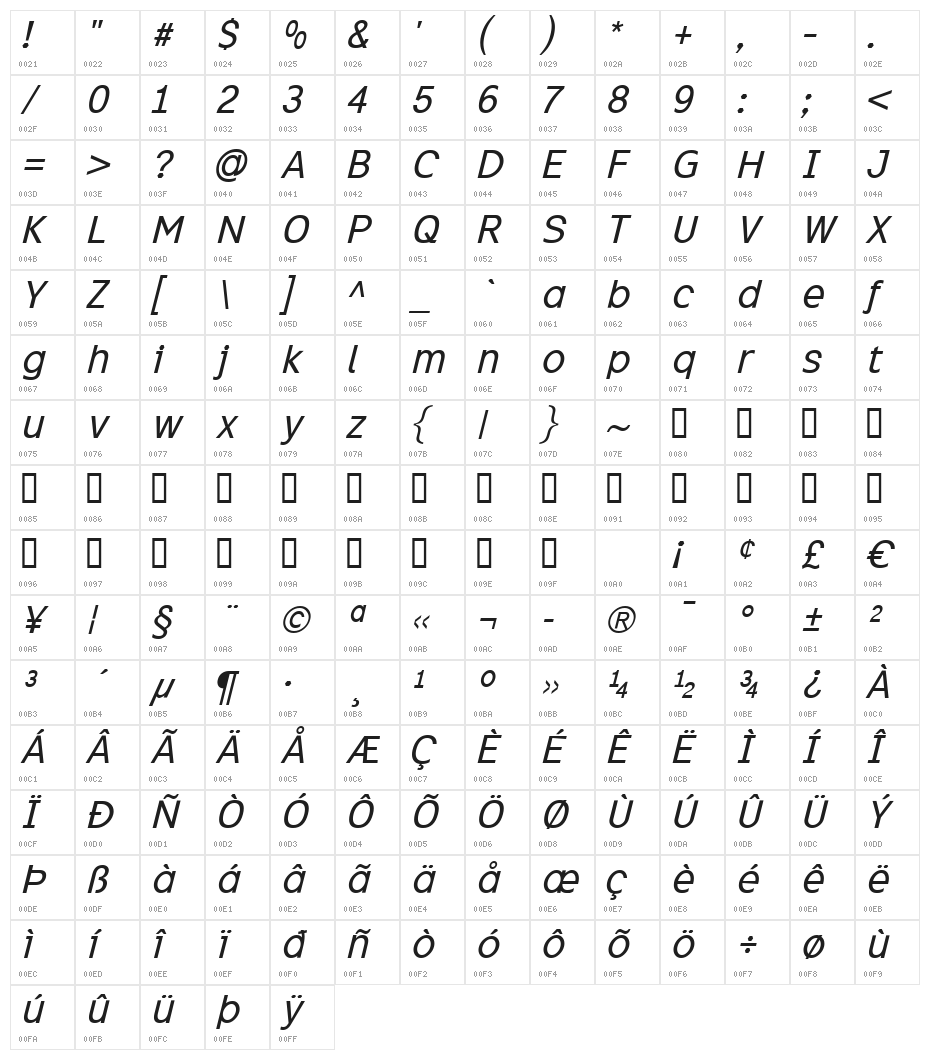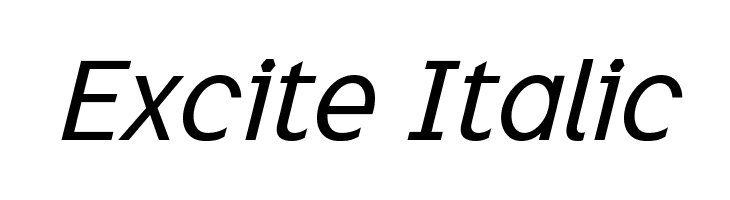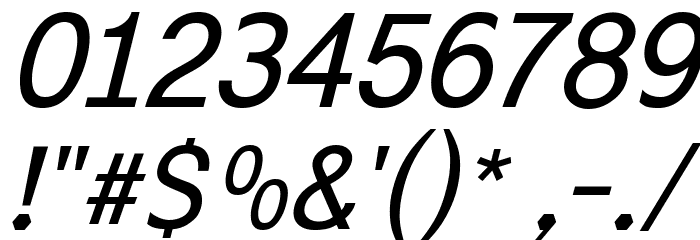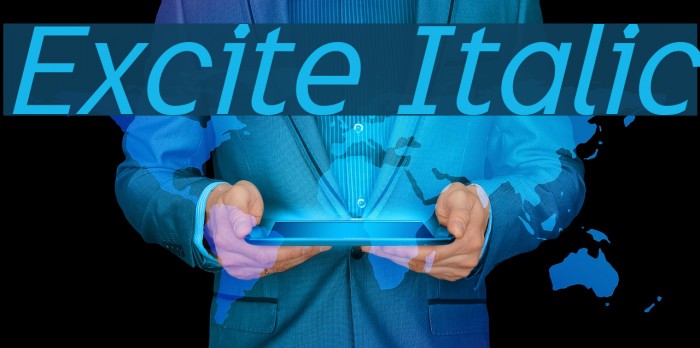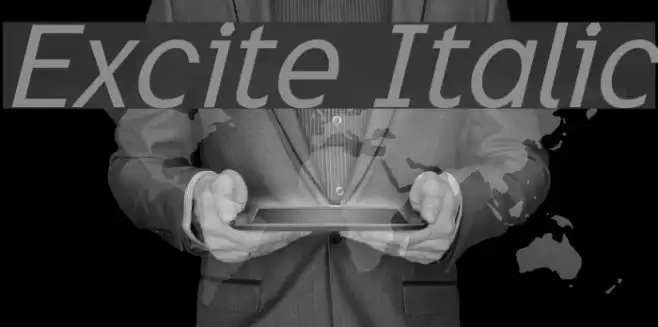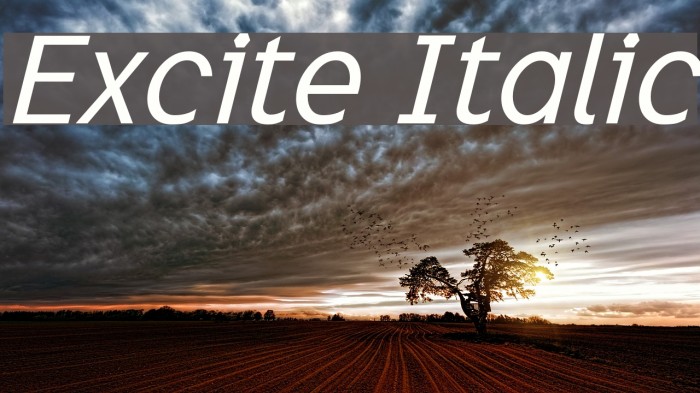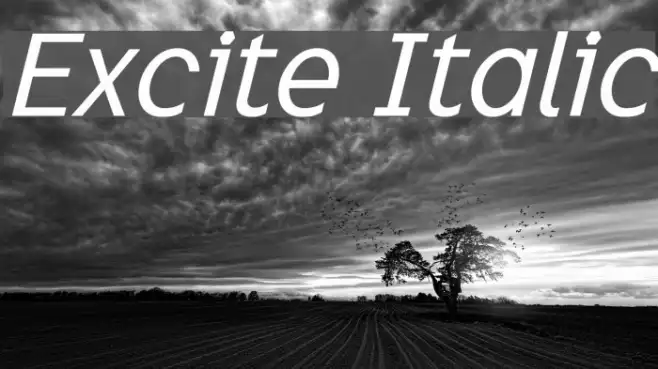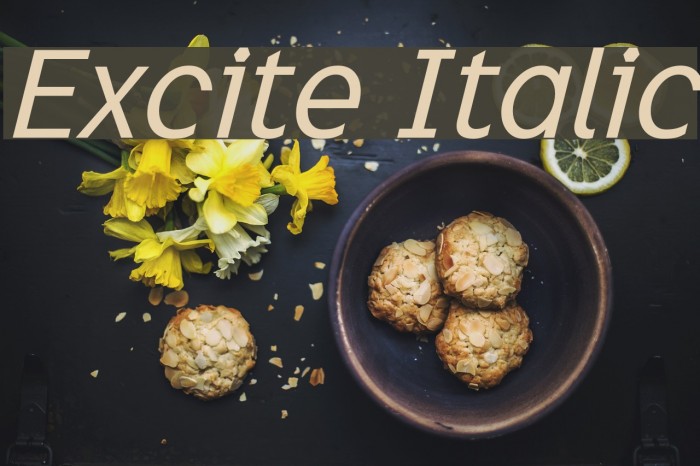
Excite Italic Font
| Projets proposés | Ideal for branding, advertising, and editorial design projects that require a modern and dynamic touch. |
Excite Italic